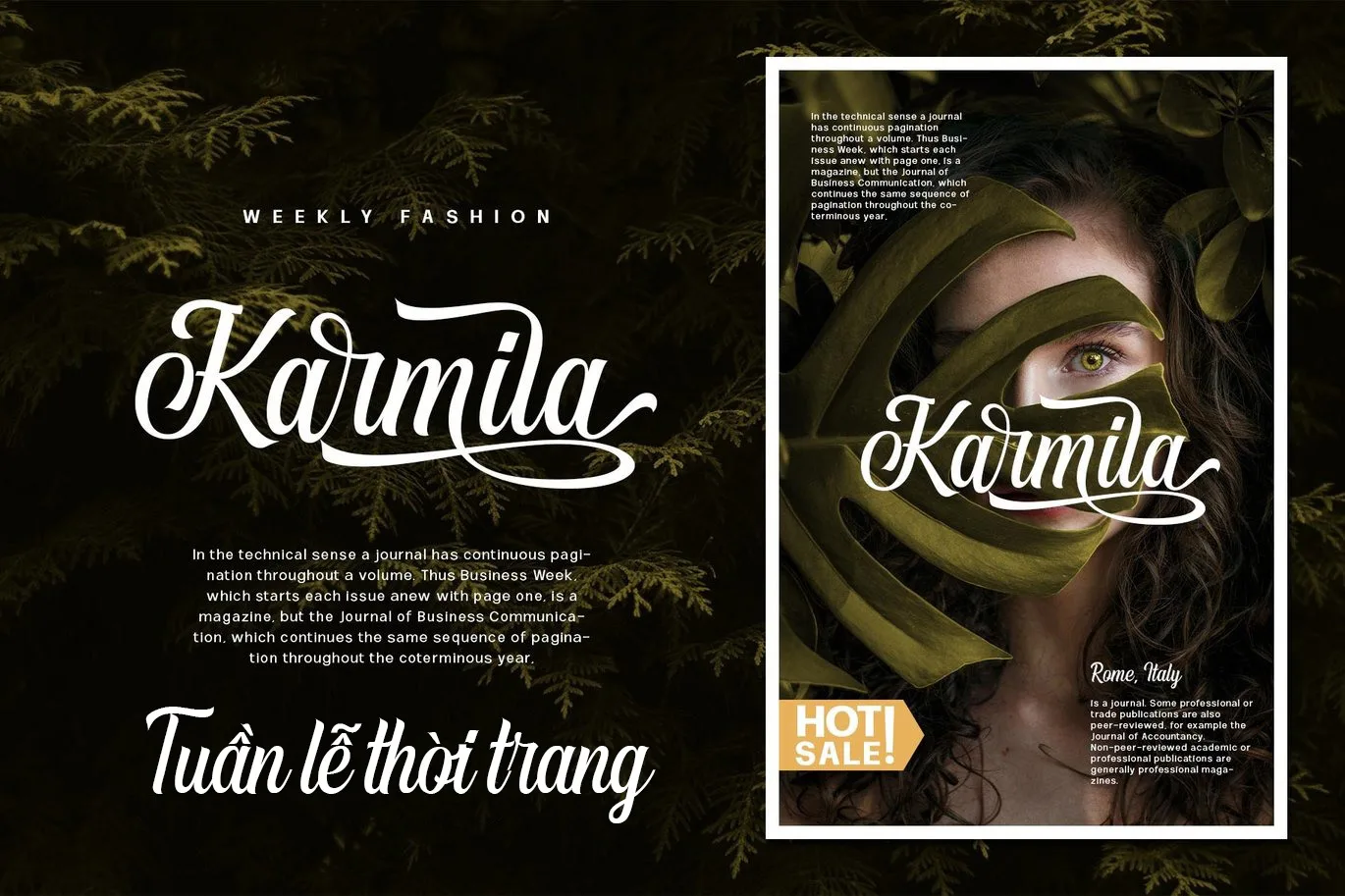
DVN Kontac Việt hóa – Font chữ uốn lượn tuyệt đẹp
Font Kontac mang phong cách viết tay với các nét chữ uốn lượn mềm mại, tạo cảm giác tự nhiên và dễ chịu cho người nhìn. Các đường nét dày dặn, kết hợp với những đường cong tinh tế, giúp font nổi bật với sự thanh lịch và uyển chuyển. Font này phù hợp cho nhiều mục đích sáng tạo khác nhau, đặc biệt là các thiết kế mang tính nghệ thuật và thủ công như logo, thiệp mời, tiêu đề, và các sản phẩm in ấn trang trí. Với đặc trưng của phong cách chữ script, Kontac đem đến một cảm giác thân thiện, ấm áp và gần gũi.
Phiên bản Việt hóa của font Kontac giữ nguyên vẹn tính chất bay bổng của chữ viết tay, đồng thời bổ sung đầy đủ các ký tự có dấu của tiếng Việt, giúp font trở nên linh hoạt và dễ sử dụng hơn trong các thiết kế đồ họa tiếng Việt. Đây là một lựa chọn lý tưởng cho những ai đang tìm kiếm sự sáng tạo và tính cá nhân hóa trong các dự án thiết kế.
Font có hỗ trợ Ligature và Glyphs giúp bạn tạo ra hiệu ứng chữ hoa lá, xem hướng dẫn dùng Ligature và Glyphs tại đây